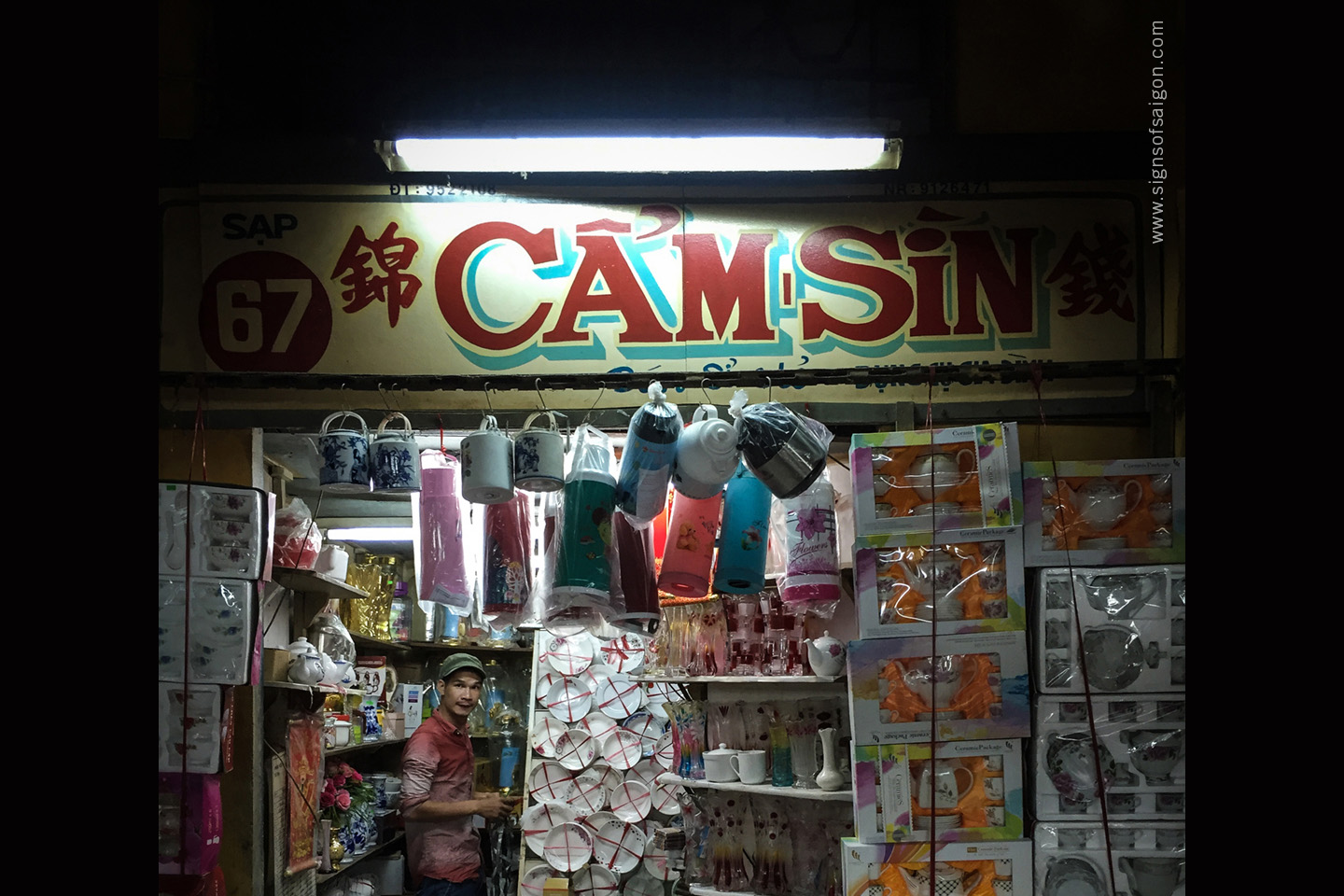
Saigon ist eine Megastadt mit mehr als 10 Millionen Einwohnern, das wirtschaftliche Zentrum einer ehemals französisch kolonialisierten, sozialistischen Republik mit kapitalistischer Marktwirtschaft. Saigon ist eine Stadt der Gegensätze, eine Stadt mit einer bewegten Geschichte und eine Stadt, die sich auf dem Weg in die Zukunft fast selbst überholt. All dies zeigt sich im Stadtbild, in der Architektur, in den Märkten, aber auch in der Typografie im Stadtraum.
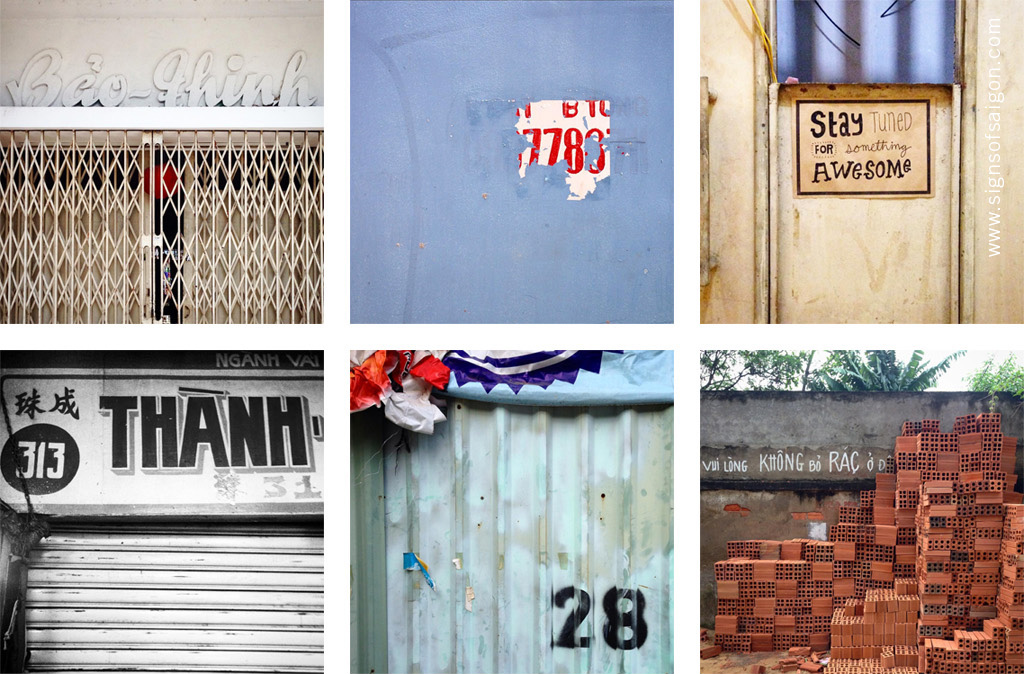
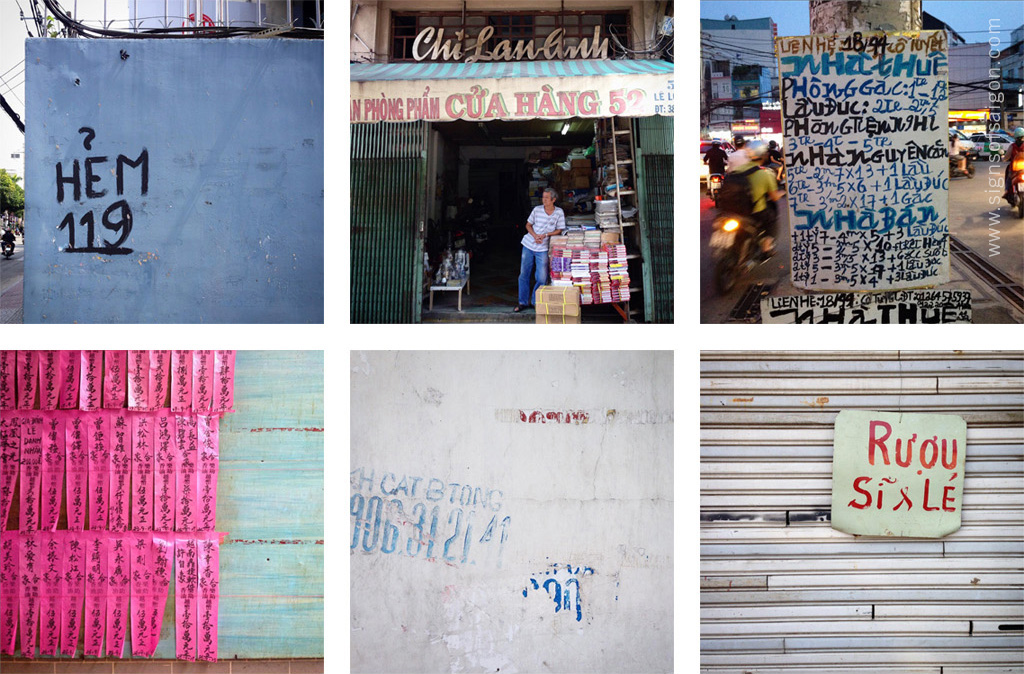
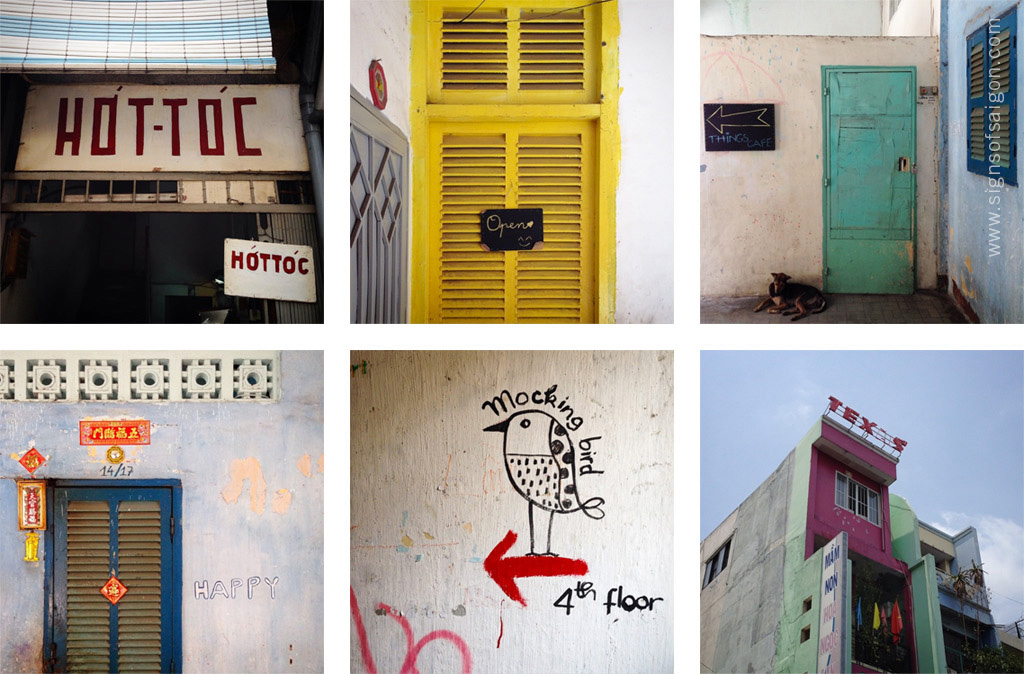
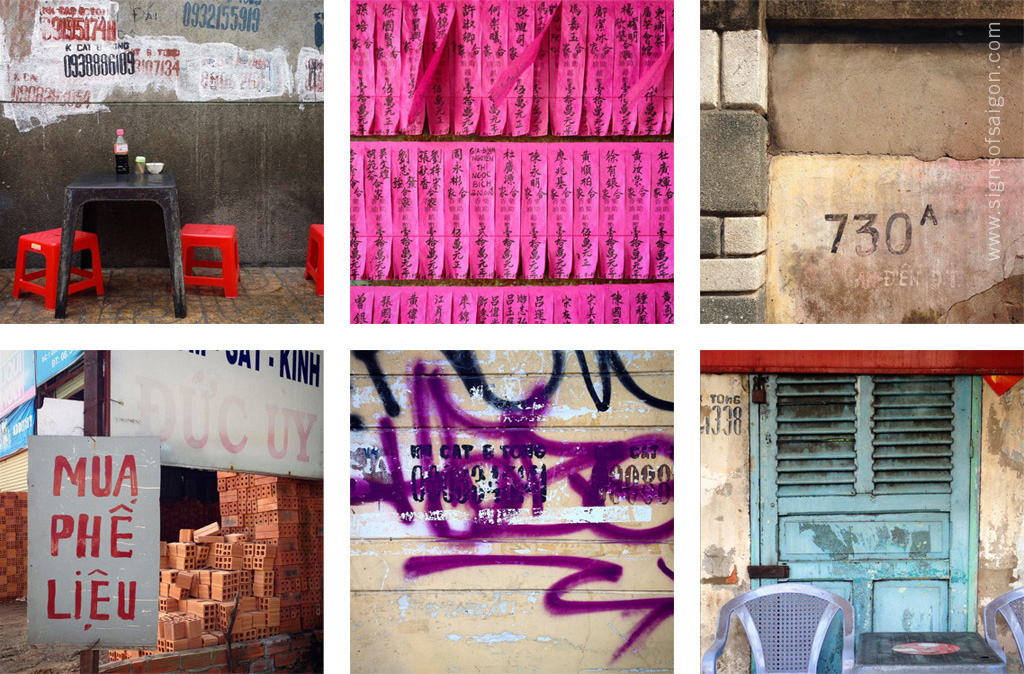
Dokumentation typographischer Ereignisse im Stadtraum
Entdeckungen und Untersuchungen zum Thema „Handschrift“